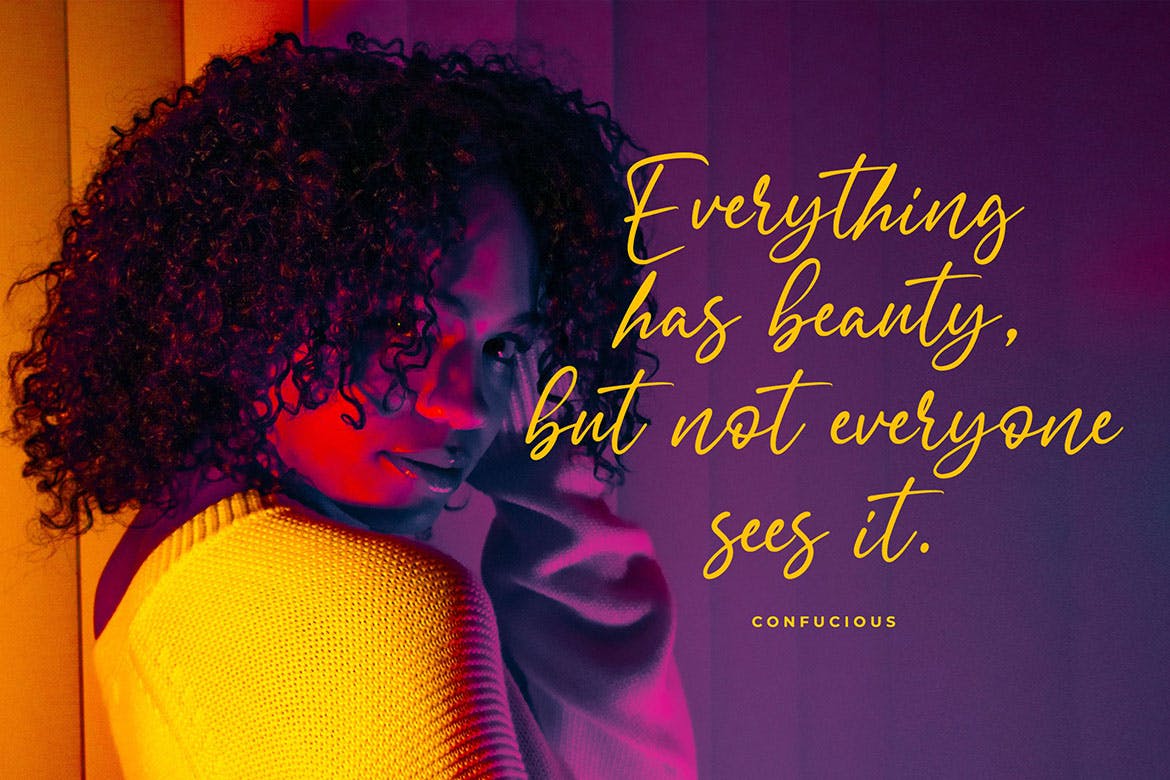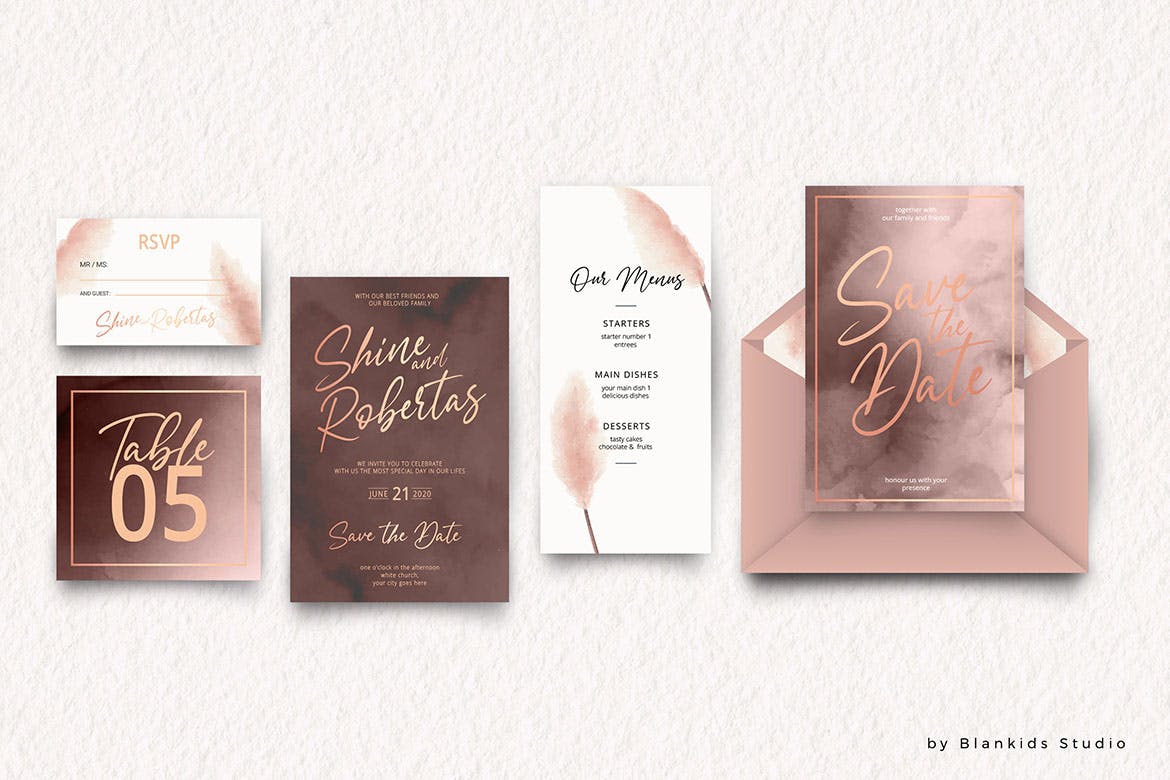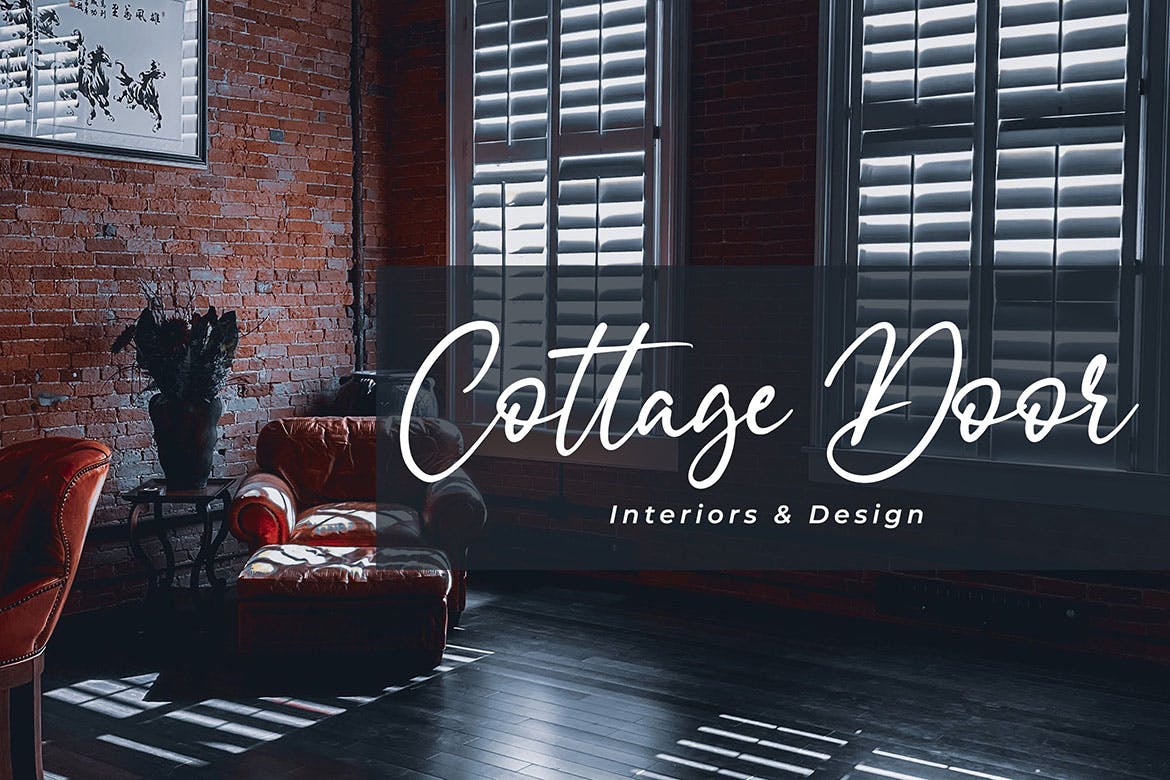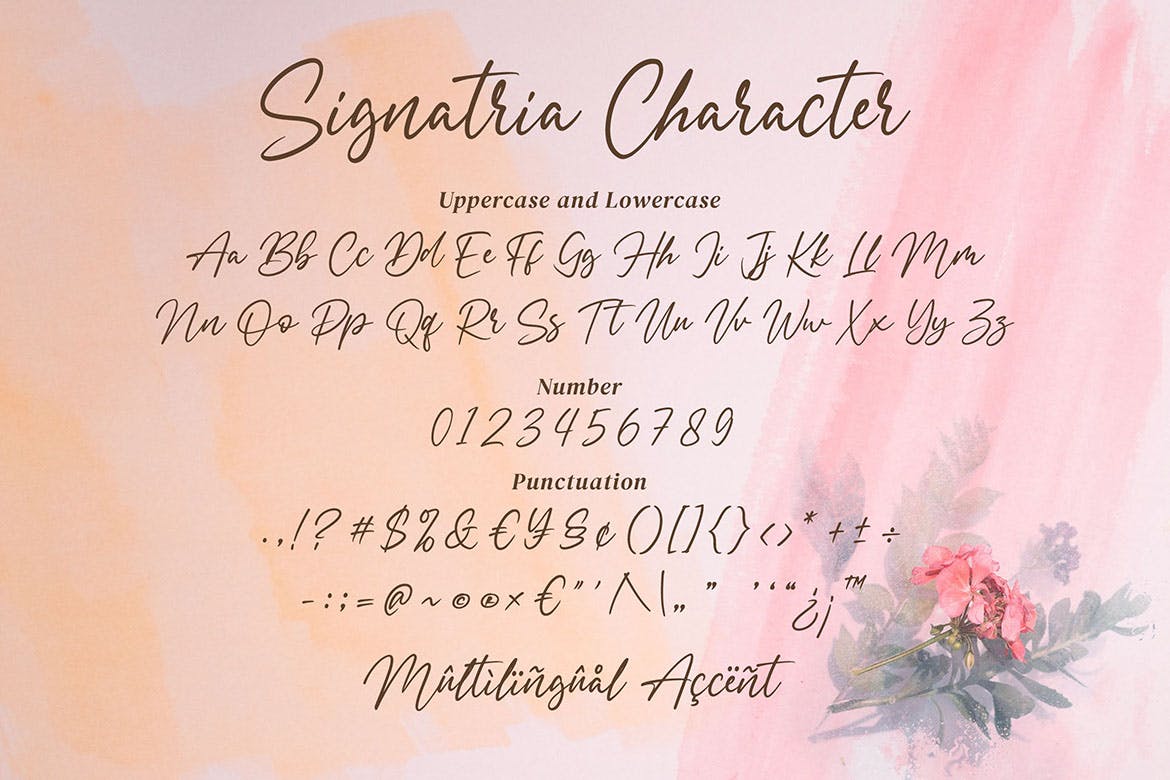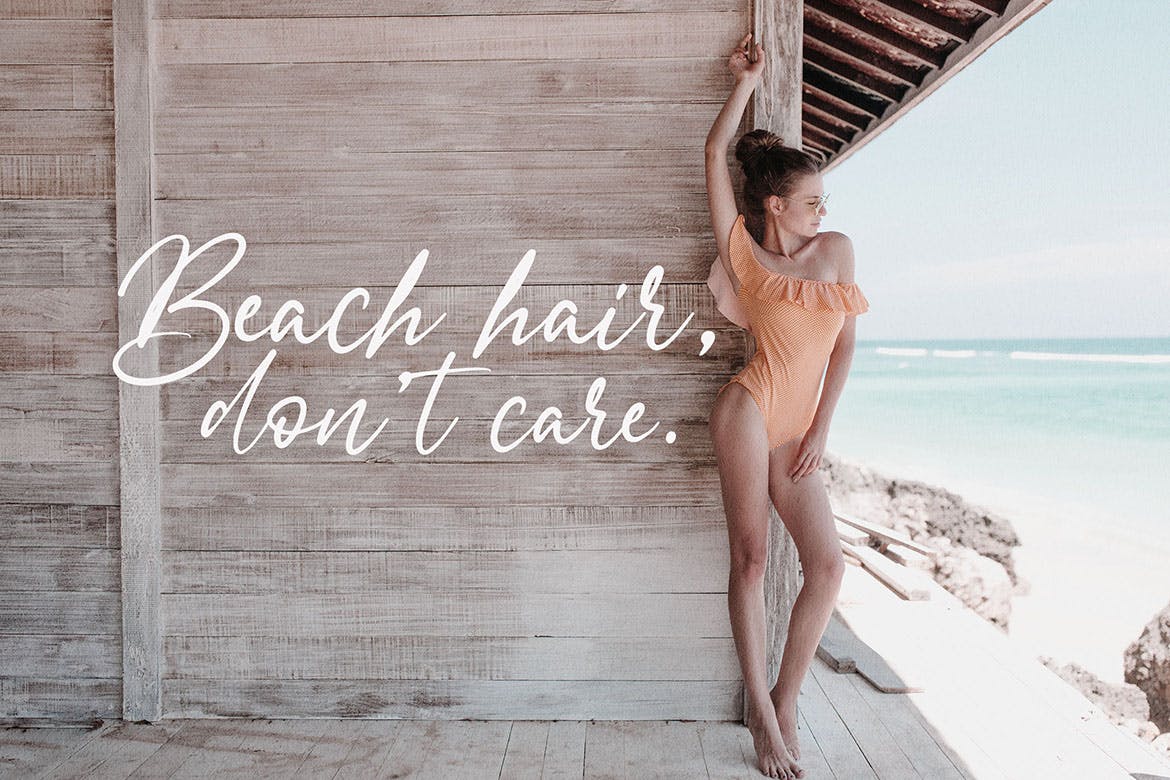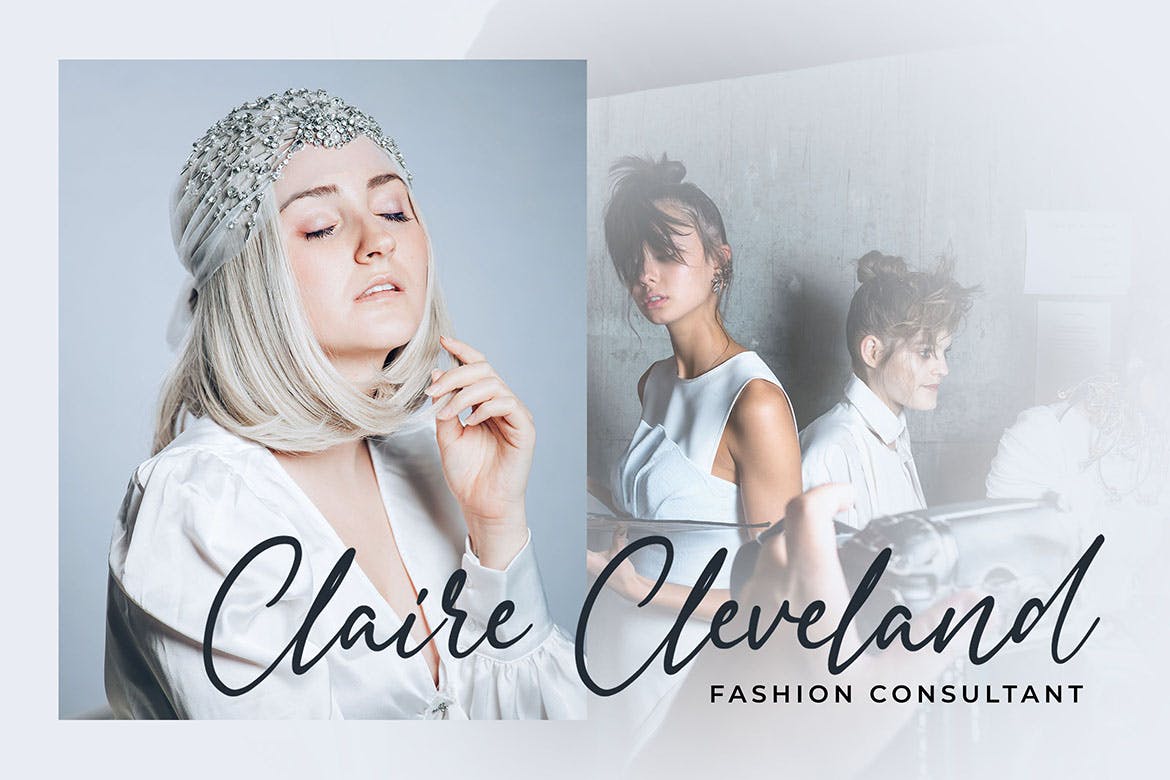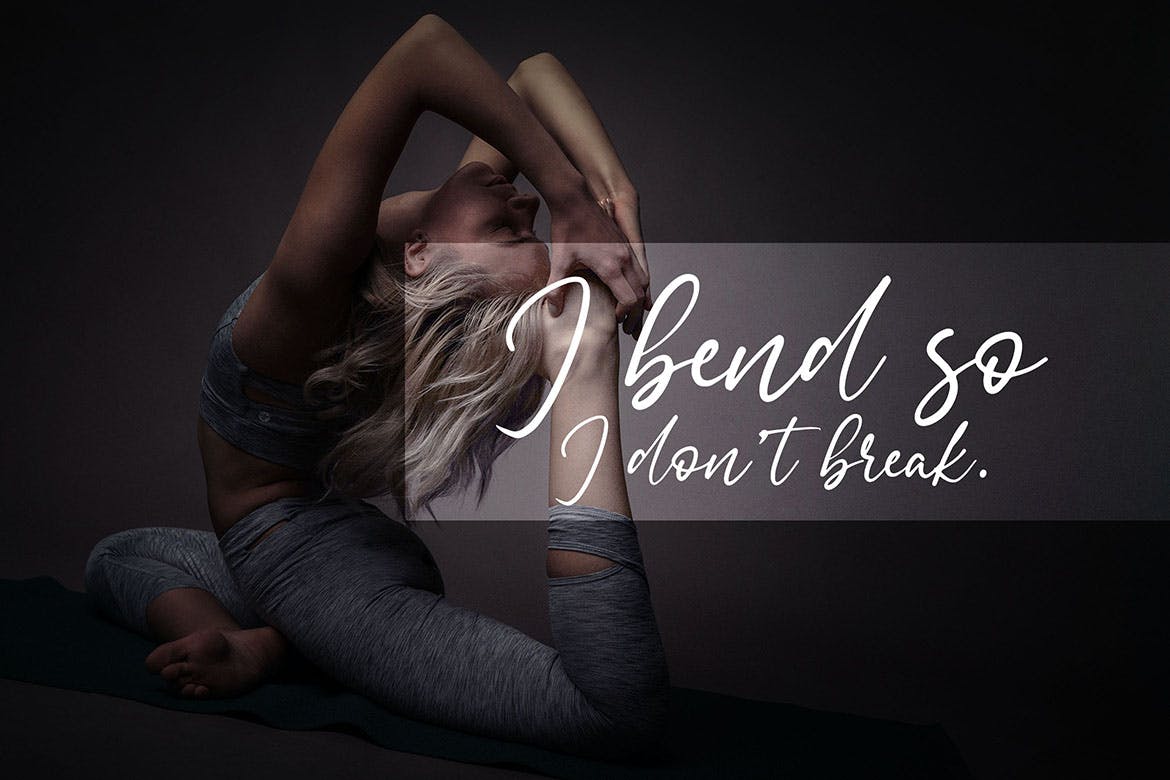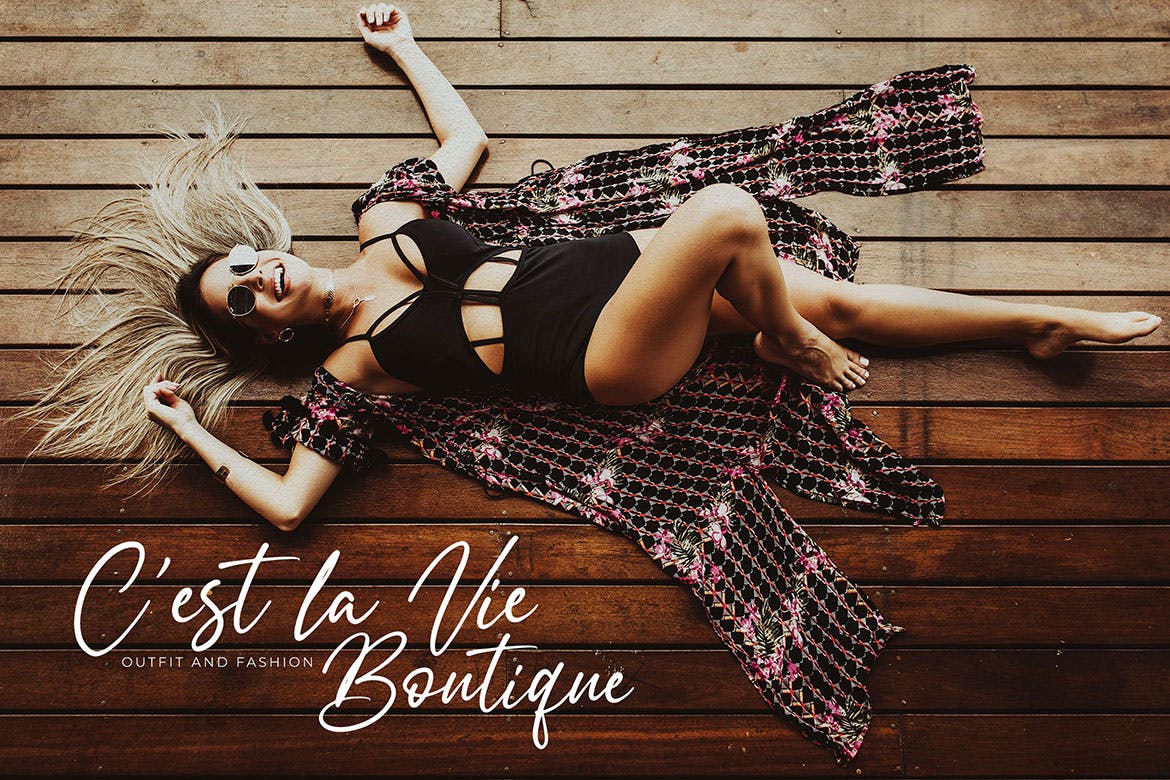
معرفی محصول جدید ما، فونت Signatria، یک فونت شیک و جذاب است. این فونت با الهام از سبک امضا طراحی شده و موضوعی سرگرمکننده دارد که برای نمایش، طراحی تیشرت، پروژههای هنری، تابلوهای نقل قول، لوگو و غیره بسیار مناسب است.
توجه: این فونت به دلیل قابلیتهای چند زبانه و طراحی منحصر به فرد، گزینهای عالی برای هر پروژهای است.